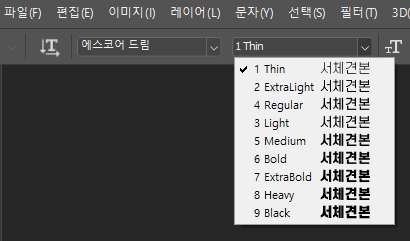
에스코어 드림 (S-Core Dream) 글꼴(폰트)은 Thin, Extra Light, Light, Regular, Medium, Bold, Heavy, Black의 무료 9가지 두께를 지원하고 있습니다.
현대적 감성과 복고와의 조화로움을 강조하며 완성도 높은 고딕 스타일의 활용도 높은 글꼴이 무료라니 여간 반가운 일이 아닐 수 없습니다.
포토샵에서 에스코어 드림 (S-Core Dream) 글꼴 선택 시 위와 같이 한 번에 9가지 두께를 원하는 대로 선택할 수 있습니다.